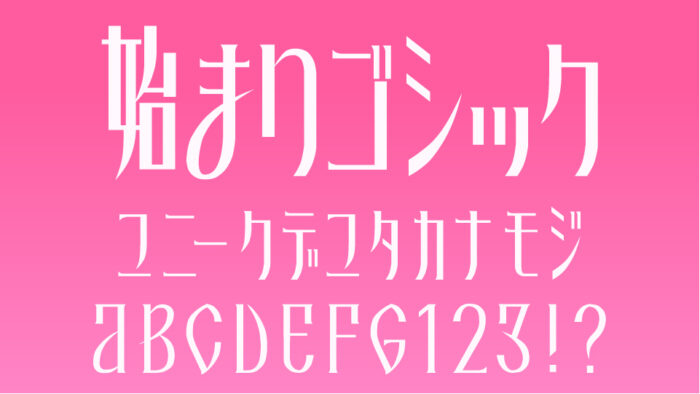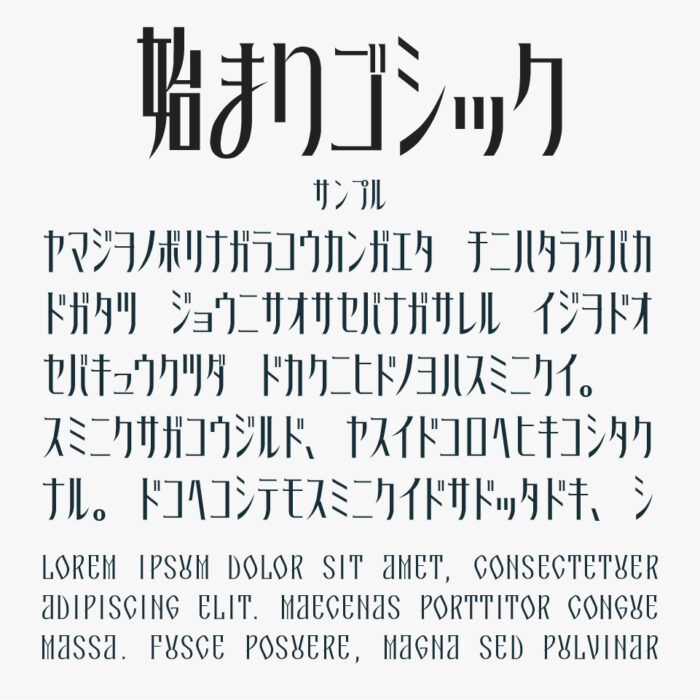
始まりゴシック
始まりゴシックフォントは、劇場版魔法少女まどか☆マギカのロゴをモチーフにしたデザインフォントです。
縦に長くシャープなシルエットが特徴的な、スラッとスタイリッシュな雰囲気を持つフォントです。
理知的でクールな印象もありながら、クラシカルでカッコ良さもあるデザインがとってもステキです。魔法少女がベースにありますが、SF的・近未来的なデザインにもマッチしそうです。
収録文字は、カタカナ・アルファベット・数字・記号が収録されています。現在ベータ版として配布されているので、今後アップデートされる可能性があります。